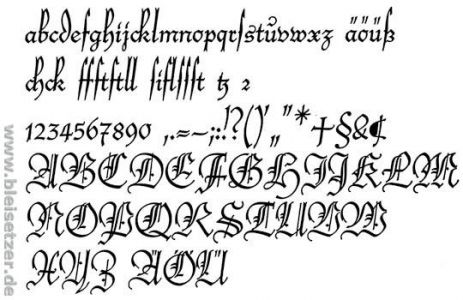
Trenn=strich oder Trenn-strich oder ...
Ich mache gerade ein Buch, in dem viele alte Zitate sind. Es geht darin unter anderem auch um »Gebeth= und Hand=Büchlein«. Aber das Gleichzeichen will mir nicht gefallen. Und in der umfangreichen Adobe Garamond Pro (OT) habe ich ein entsprechend angepasstes Trennzeichen bisher nicht gefunden.
Was tun in einem solchen Fall? = oder - oder eine andere Variante??
Ich verstehe deine Frage nicht wirklich, wie meinst du das mit »Gebeth= und Hand=Büchlein« ? Aber hast du es mit dem Divis, Geviert- oder Halbgeviertstrich schon versucht? Die sind alle ähnlich dem Gedankenstrich, nur werden sie in unterschiedlicher Weise angewandt.
Es geht konkret darum, ob ich »Gebeth= und Hand=Büchlein« (wie im Manuskript) oder »Gebeth- und Hand-Büchlein« schreibe. Geviert- oder Halbgeviertstrich fallen meiner Meinung nach eh raus.
Ich würde auf jeden Fall die modernisierte Variante wählen, denn das Gleichzeichen provoziert eher Missverständnisse und das Werk wäre im Zweifelsfall auch in Datenbanken und elektronischen Bibliothekskatalogen eher mit der Standardschreibweise auffindbar.
Es gibt ja durchaus (im Moment fallen mir nur Gebrochene ein) Schriften, in denen das Divis als Doppellinie dargestellt wird, z.B. die
Heinrichsen-Kanzlei
J.D.Trennert & Sohn, Hamburg-Altona
Erstguß 1933
Friedrich Heinrichsen
Aber das ist halt die Darstellung des Divis in dieser Schrift und kein mathematisches Gleichheitszeichen.
Deine jetzt verwendete Schrift stellt ein Divis sicher nicht als Doppellinie dar, also hast Du doch eigentlich auch kein Problem. Es wäre doch nicht richtig, statt eines Divis ein anderes Zeichen zu verwenden.
Es gibt schon noch ein paar moderne Fonts, die den Doppelbindestrich enthalten. Aber ob man das gemischt einsetzen sollte, ist fraglich.
Es ist schließlich nur eine stilistische Variante und nicht etwas, was zum Beispiel innerhalb eines Titel-Eigennamens übernommen werden müsste.